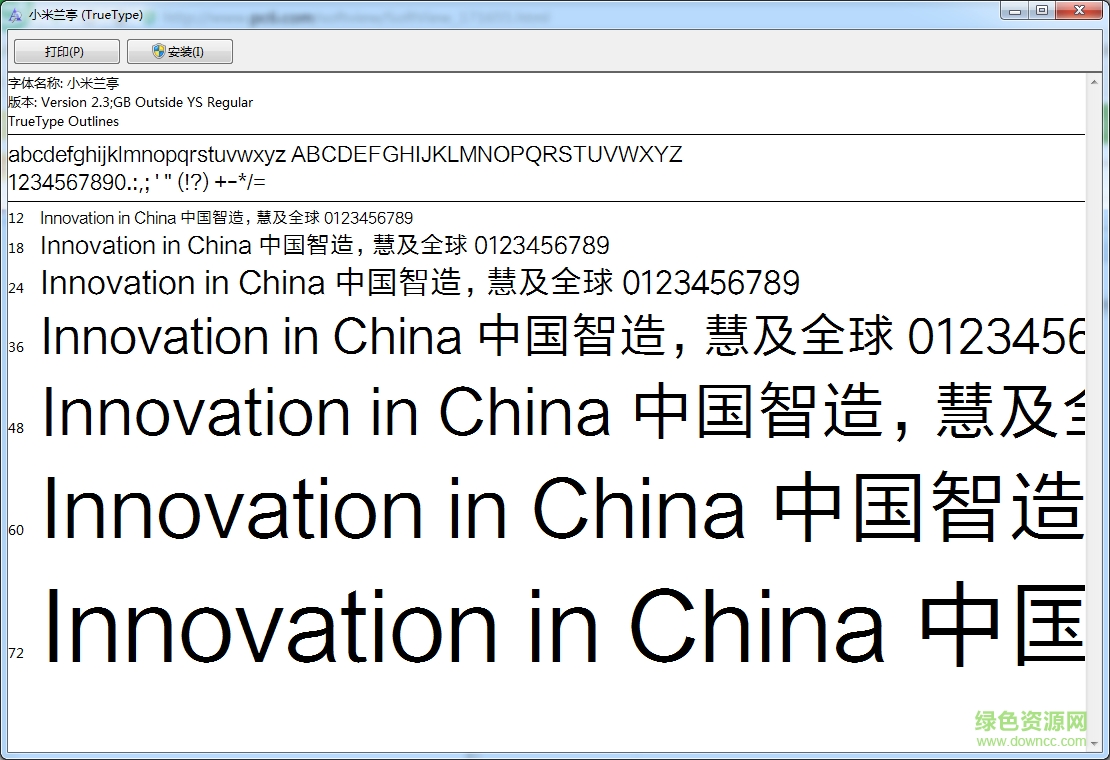
小米蘭亭黑體是一款極具美感的電腦字體,字體纖細(xì)簡(jiǎn)單,適用于多種行業(yè)領(lǐng)域,可直接導(dǎo)入多種設(shè)計(jì)軟件中使用??靵?lái)綠色資源網(wǎng)下載體驗(yàn)吧!
小米蘭亭黑字體TTF官方下載是MIUI 8 系統(tǒng)自帶字體 TTF 格式,非常適合在手機(jī)上使用。小米蘭亭字體經(jīng)過(guò) 18 個(gè)月精心打磨,從中宮調(diào)整,到重心設(shè)計(jì),特別為了手機(jī)屏幕以及移動(dòng)互聯(lián)網(wǎng)!